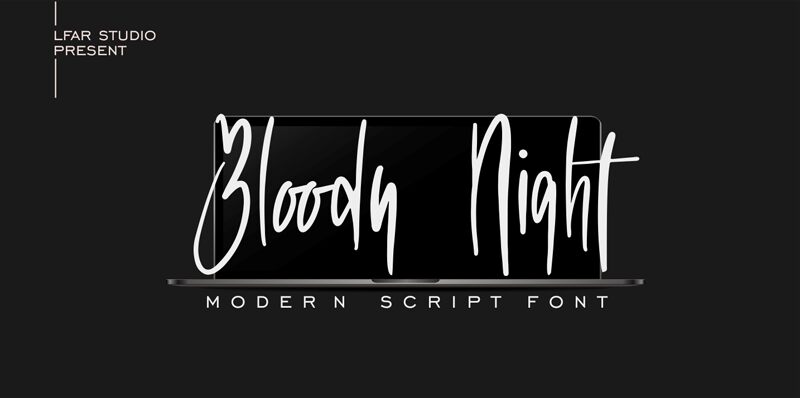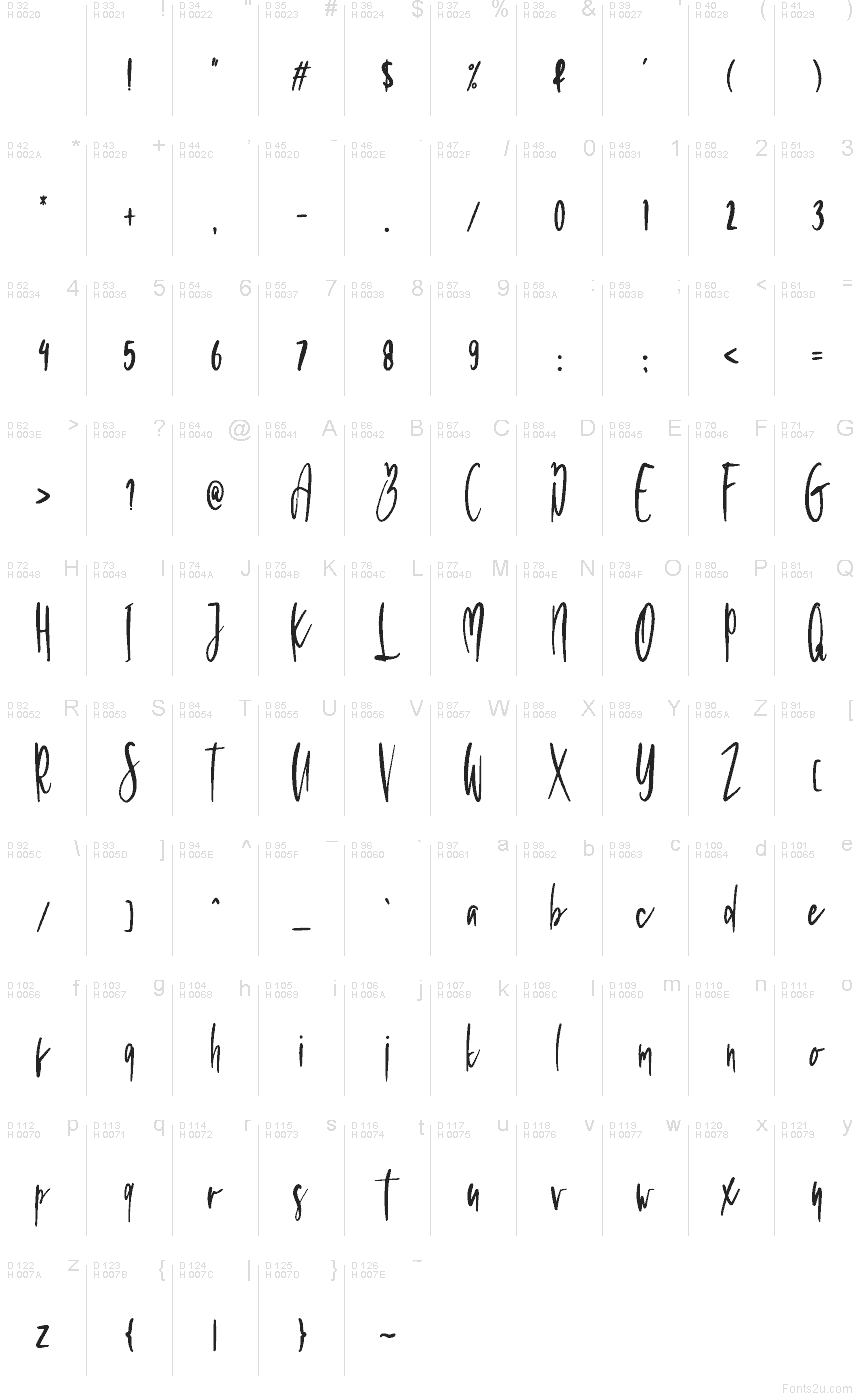
Bloody Night
Bloody Night من استوديو Lfar Studio هو خط يدوي مجاني بطابع الرعب، يتميز بضربات سريعة وحادة ويحمل أجواء ليلية مقلقة. الحروف تبدو طويلة ومشدودة، وتمزج بين الزوايا القاطعة والحلقات الرخوة، مما يجعل الكتابة تبدو كتحذير خُطَّ على عجل أكثر من كونها خطاً أنيقاً.
يناسب هذا الخط بشكل طبيعي عناوين الملصقات، وأغلفة قصص الرعب، وتصاميم الهالوين، والرسومات الموسيقية، والمنشورات الاجتماعية المظلمة حيث يحتاج الخط المجاني إلى تلك اللمسة الخام واليدوية. استخدمه للعناوين القصيرة، أو بطاقات العناوين، أو الشعارات عندما تريد أن تضفي تلك الجودة التي تشبه "الملاحظة المكتوبة في وقت متأخر" على الأجواء العامة لتصميمك.